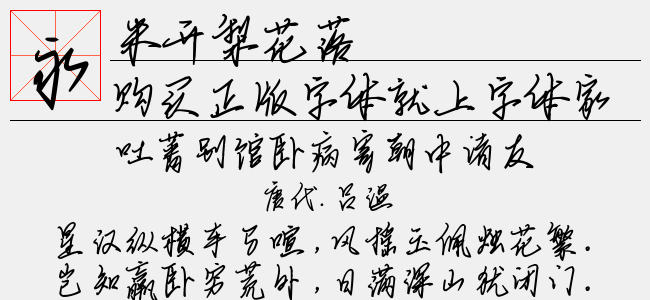
书体坊禚效锋行草体.ttf
书体坊禚效锋行草体.ttf是一款非常漂亮的艺术字体,书体坊禚效锋行草体.ttf字体广泛用于各种书刊、画册的设计印刷中,书体坊禚效锋行草体.ttf字体具有强烈的视觉冲击力,报纸和杂志和书籍中常用字体, 海报、个性促进品牌标志设计、字体设计、等
书体坊禚效锋行草体.ttf是一款非常漂亮的艺术字体,书体坊禚效锋行草体.ttf字体广泛用于各种书刊、画册的设计印刷中,书体坊禚效锋行草体.ttf字体具有强烈的视觉冲击力,报纸和杂志和书籍中常用字体, 海报、个性促进品牌标志设计、字体设计、等环境。 书体坊禚效锋行草体.ttf字体是一款用于标题设计方面的字体,由字体下载站提供免费下载,字体下载大全提供最全最新的中、英文字体素材。